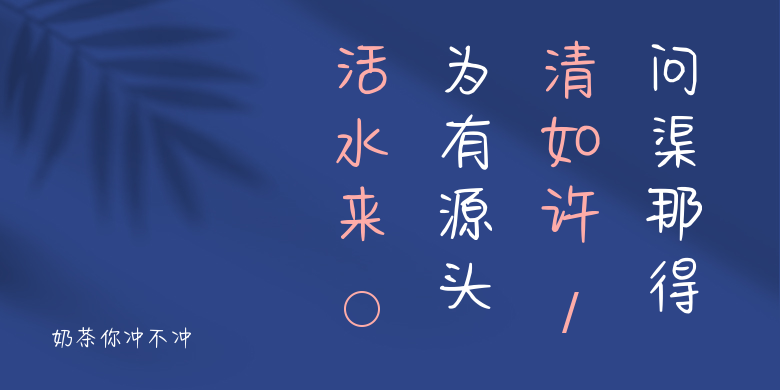
奶茶你冲不冲
奶茶你冲不冲,这款字体结构工整、笔画清晰,兼顾美观与易读性,适用于标题、正文、海报、包装、LOGO 等多种场景。字形优雅稳定,风格百搭耐看,适配日常排版与创意设计,让文字呈现更舒适、更具质感。奶茶你冲不冲一笔一画,皆是细节,以均衡的比例、流畅的线条打造舒适视觉体验,字形端正大气,风格简约现代。无论是商业设计、品牌宣传还是日常排版,都能轻松驾驭,让文字更有格调与力量。奶茶你冲不冲字体下载。